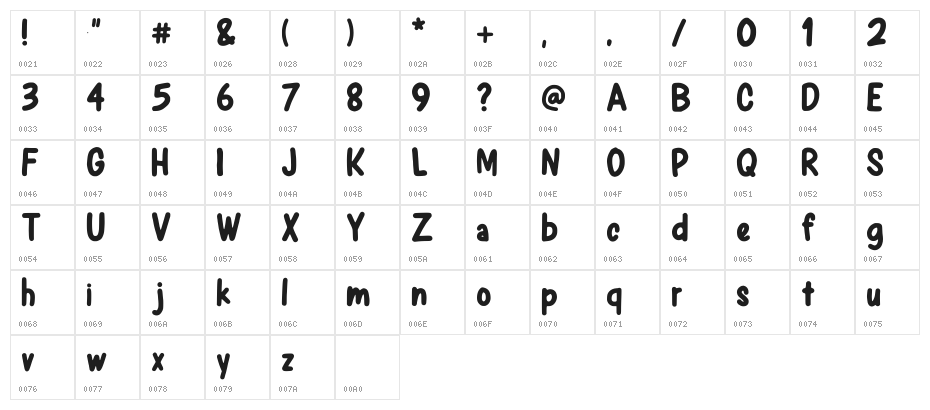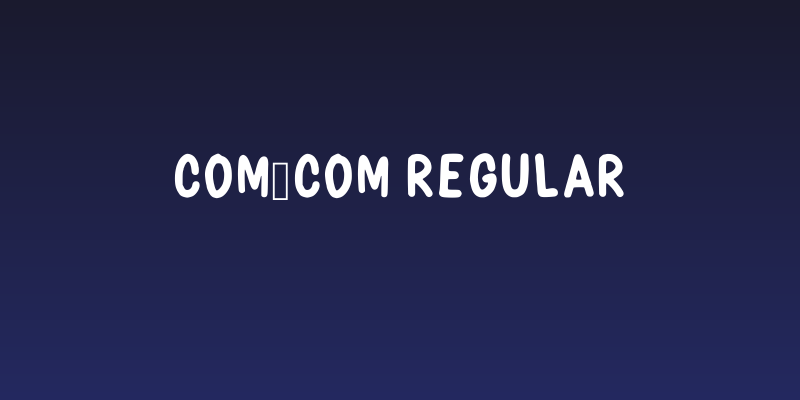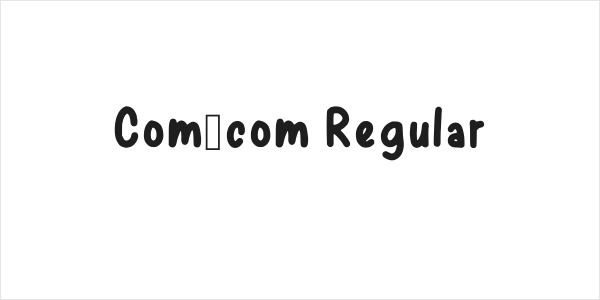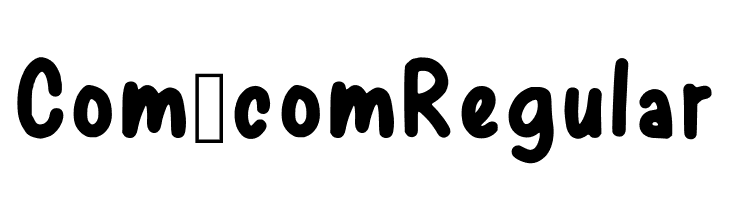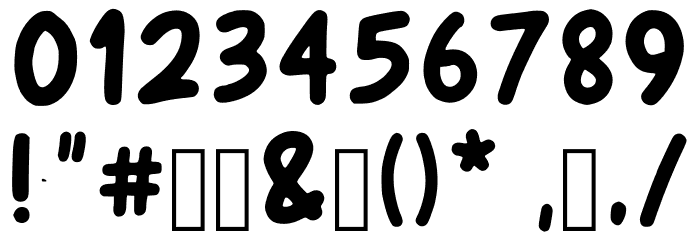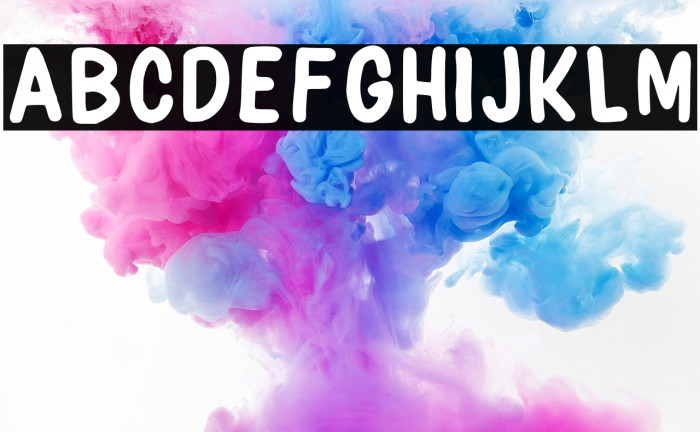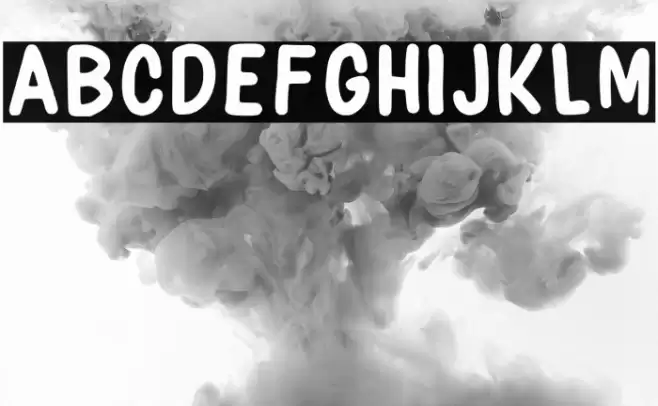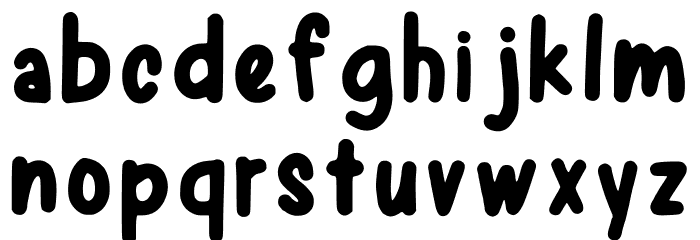
Com_com Regular Font
| Categorie | Comic |
| Stile generale | Playful, Casual |
| Progetti proposti | Ideal for children's books, playful branding, posters, and social media graphics. |